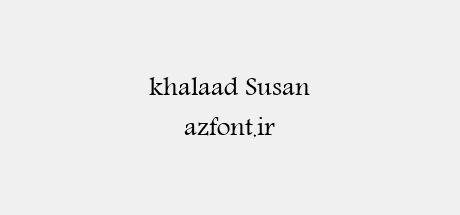
فونت زیبای رایگان khalaad Susan
قلم زیبای khalaad Susan از سری قلم های بسیار زیبا برای تایپوگرافی و لوگو تایپ می باشد.این قلم در وزن khalaad Susan و توسط Raghunath Joshi (Type Director) Vikram Gaikwad طراحی و منتشر شده است.